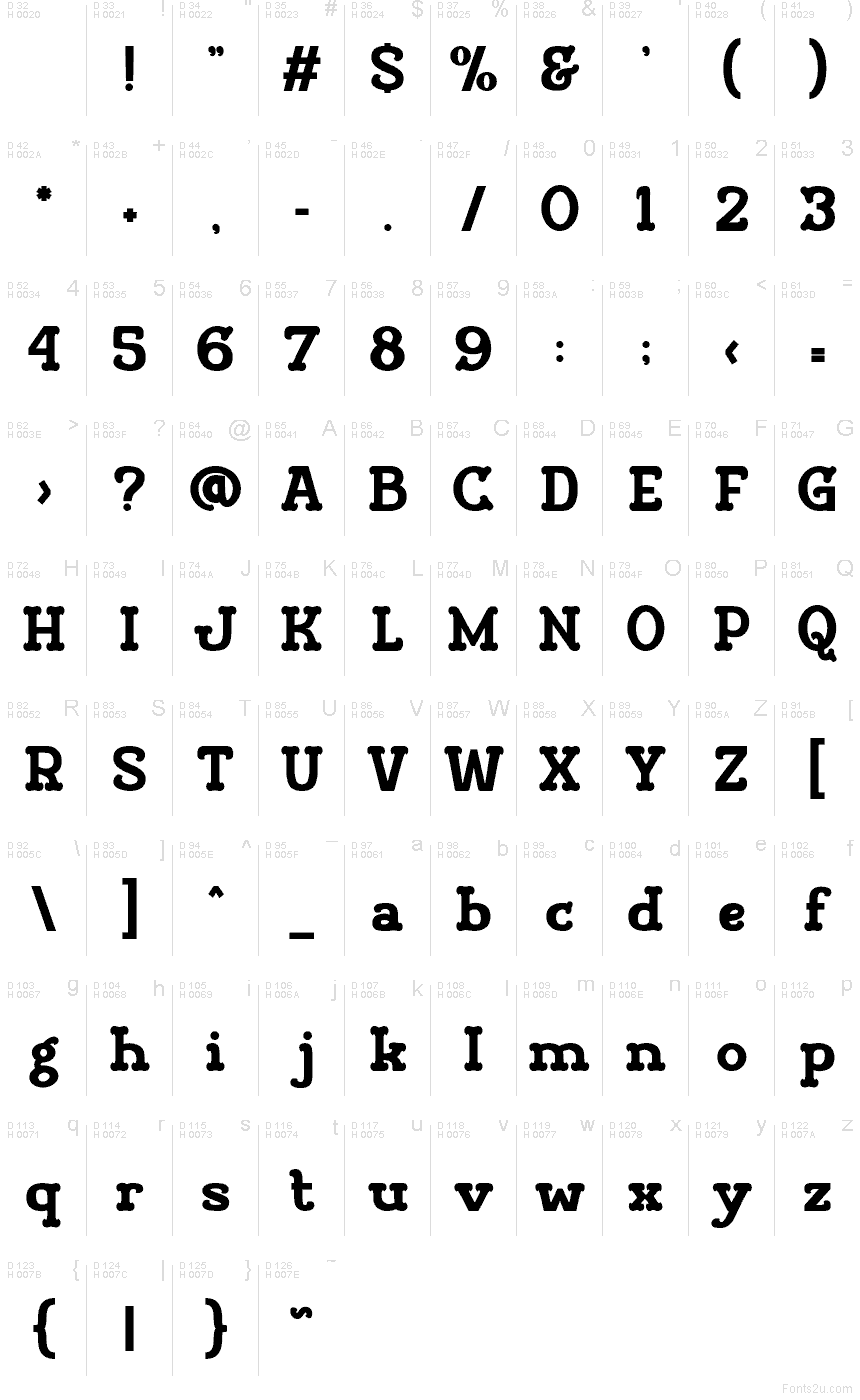
Visage Face von Putracetol Studio ist eine kostenlose Soft-Serif-Display-Schrift mit einer verspielten, retro-inspirierten Ausstrahlung. Die Buchstaben wirken kräftig und freundlich, mit bauchigen Serifen, abgerundeten Verbindungen und einem leicht schwungvollen Rhythmus, der an die Plakatgestaltung der 70er Jahre erinnert, ohne dabei zu sehr in Richtung Spielerei abzugleiten.
Sie passt hervorragend zu Branding-Projekten für Cafés oder Beauty-Labels, redaktionelle Titel, Verpackungsdesign, Musik-Flyer und überall dort, wo Wörter Wärme und Charakter brauchen. Als Free Font ist sie zudem ideal für Social-Media-Grafiken, kurze Überschriften und Monogramme, da die fülligen Serifen selbst einfachen Texten eine markante, persönliche Silhouette verleihen.